今回は、かに沢のりおさんデザインのかわいいフォントの中から5書体を選んでバンドル化した天下無敵に萌える日本語フォント集です。
「天下無敵に萌える日本語フォント集」の気になる中身
天下無敵に萌える日本語フォント集の中身を紹介していきます。ちなみに今回のバンドル内のフォントは前回のかに沢さんのフォント集とかぶっていません。前回のフォント集を購入した方も、今回のバンドルを安心して購入できますよ。
あめちゃんポップまる
飴をイメージした丸をあちこちに散りばめた、ポップで太めの丸文字フォントです。
漢字はJIS第一・第二水準・IBM拡張漢字(約6700文字)に対応しております。縦書き対応。
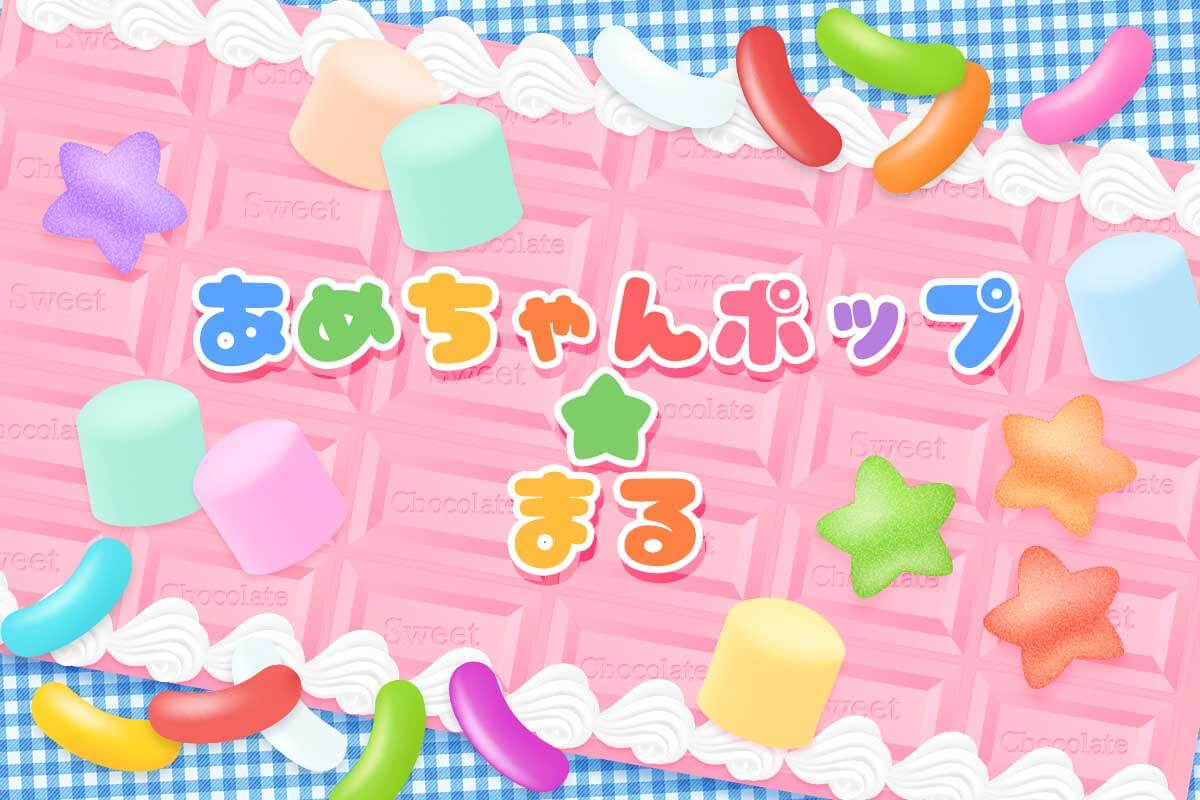
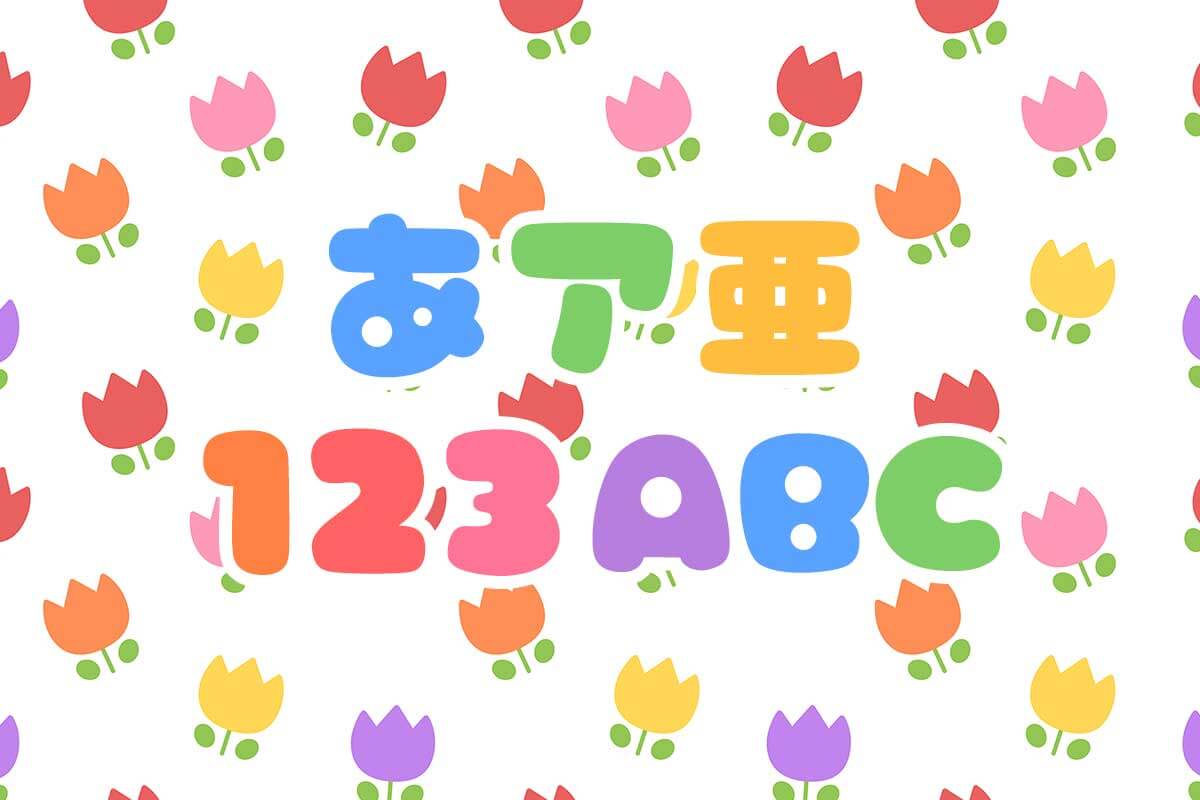
虹みんちょう
ちょっとレトロな雰囲気の明朝体フォントです。
漢字はJIS第一・第二水準・IBM拡張漢字(約6700文字)に対応しております。縦書き対応。
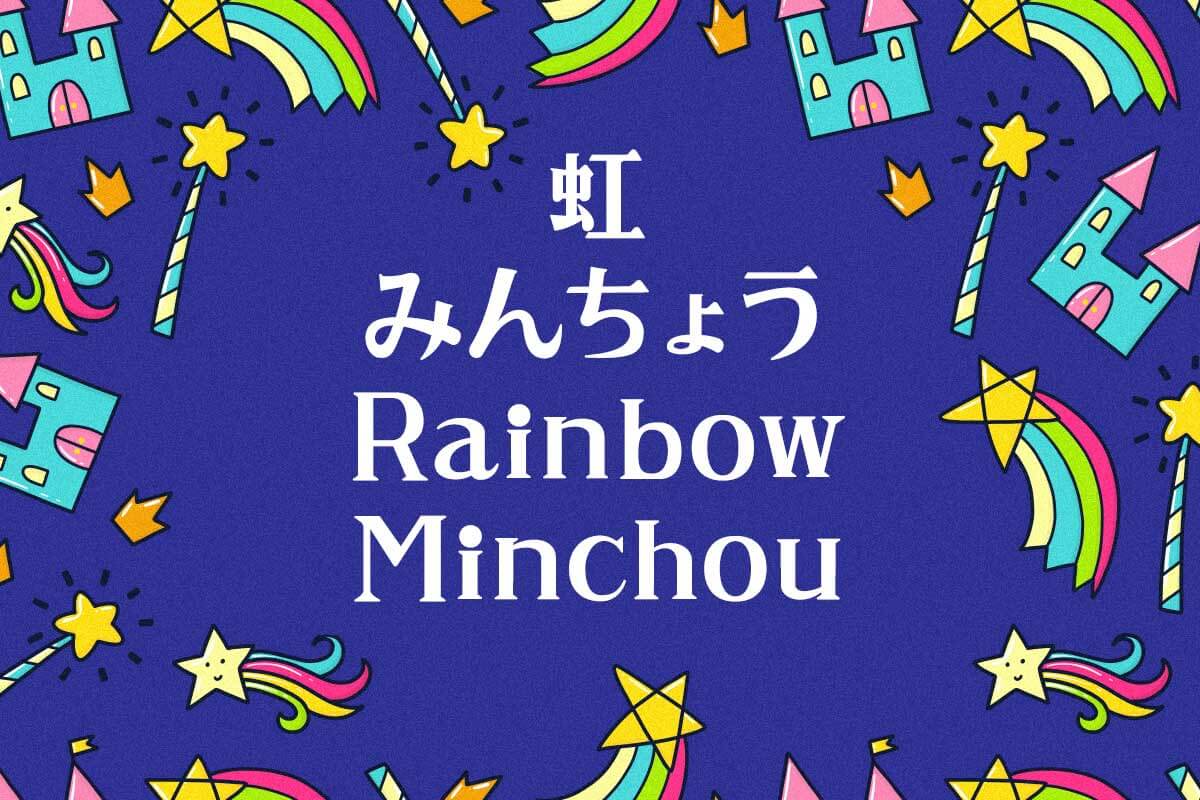
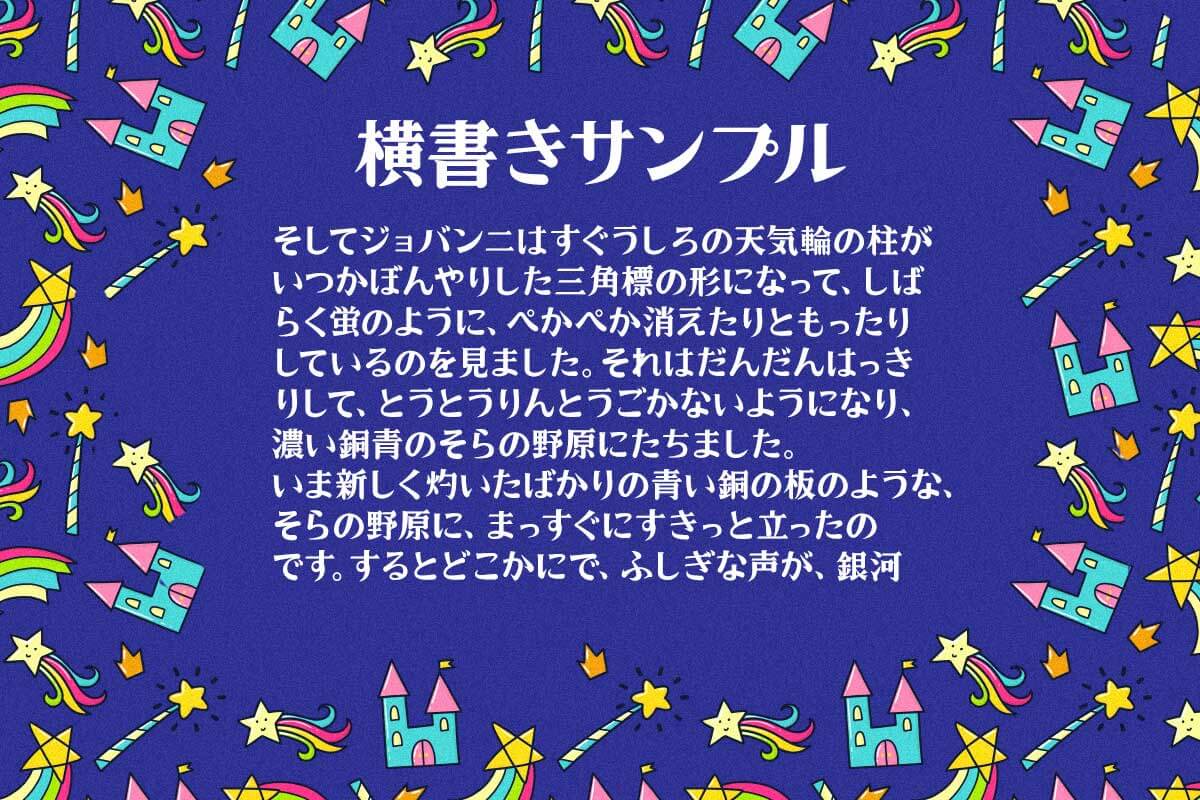
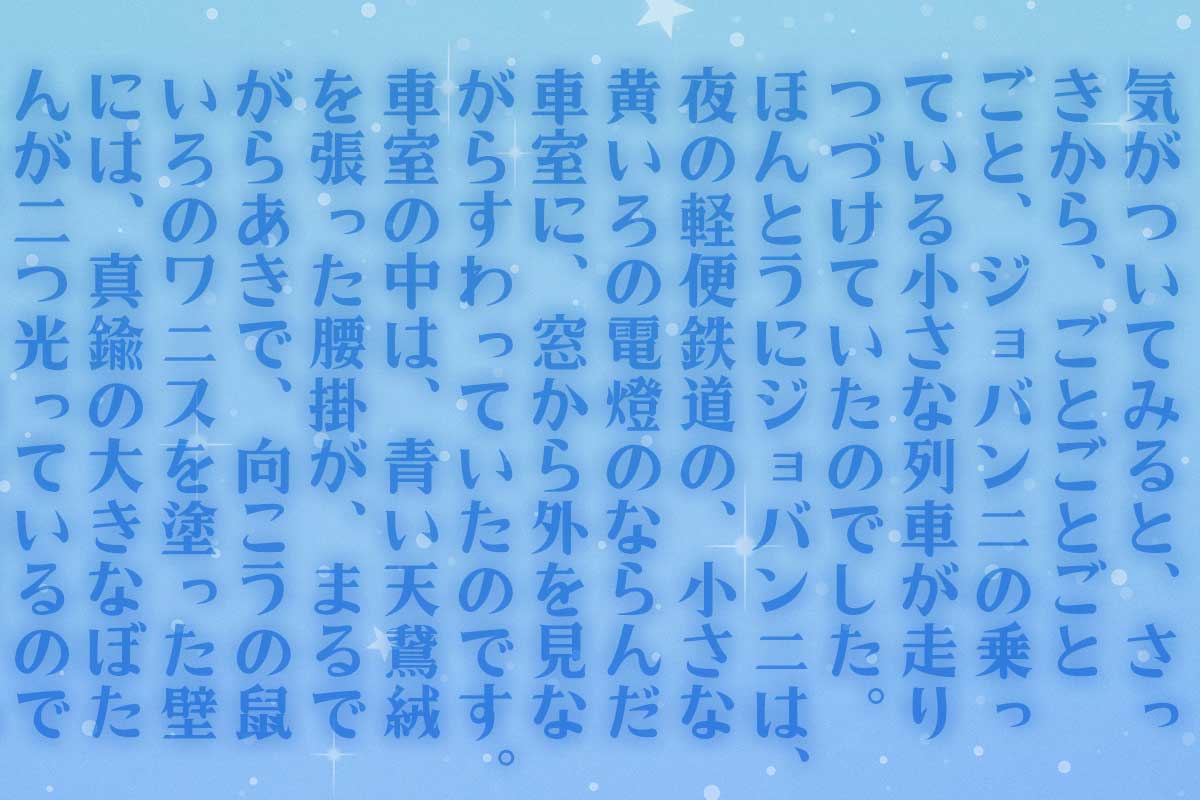
夜空みんちょう
あちこちに星やキラキラを散りばめた、夜空をイメージした明朝体フォントです。
漢字はJIS第一・第二水準・IBM拡張漢字(約6700文字)に対応しております。縦書き対応。
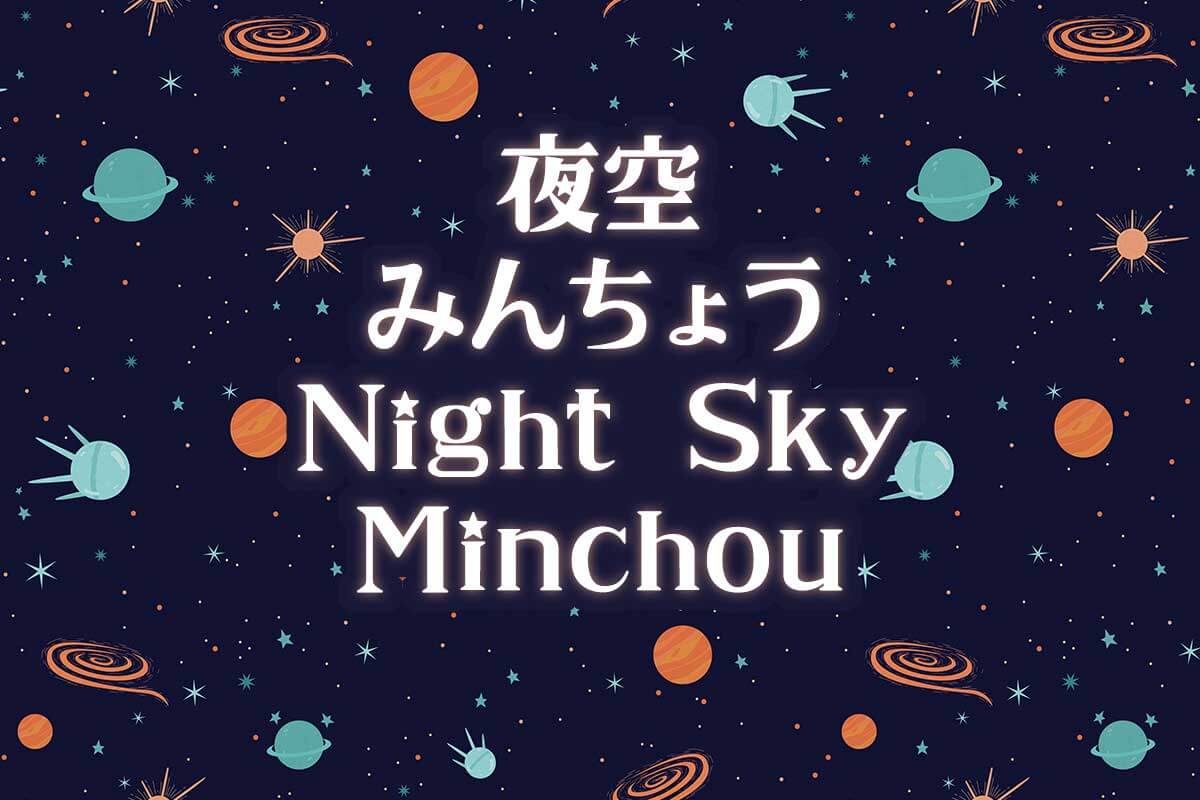
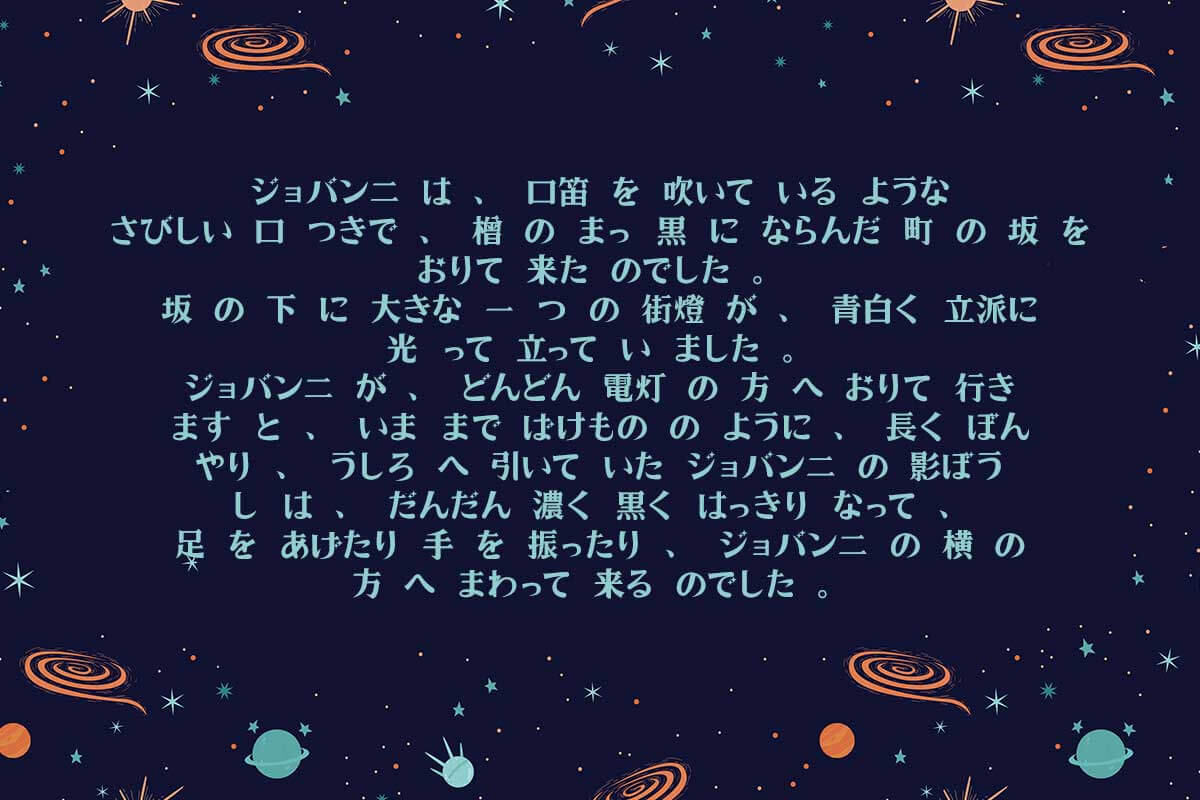
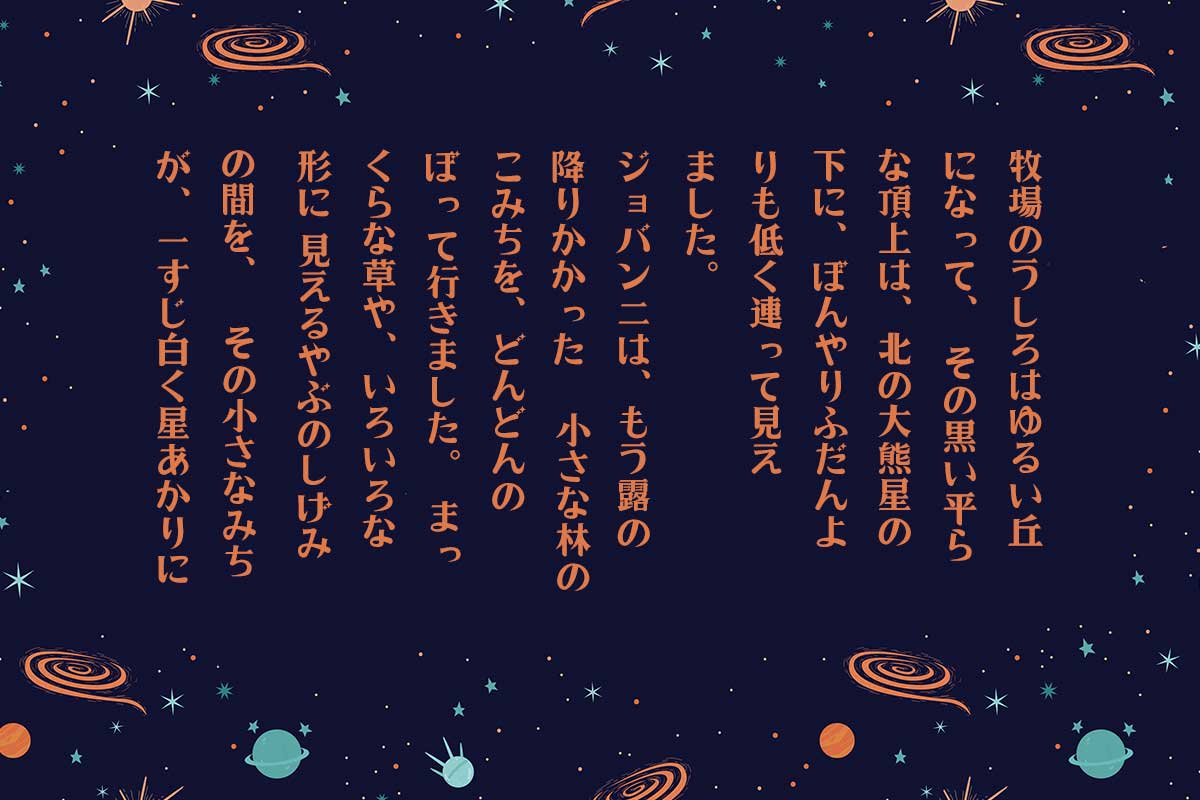
はちまるポップ
80年代に流行した丸文字をイメージしたフォントです。
漢字はJIS第一・第二水準・IBM拡張漢字(約6700文字)に対応しております。縦書き対応。
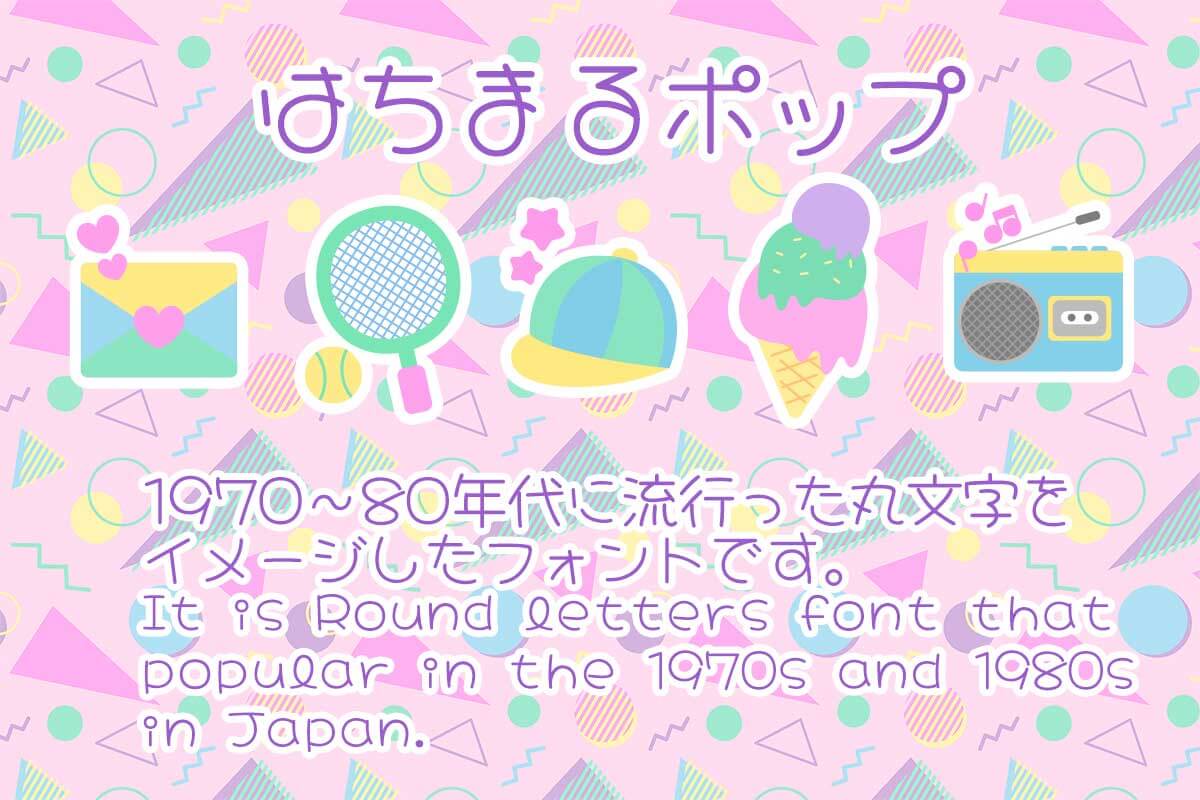
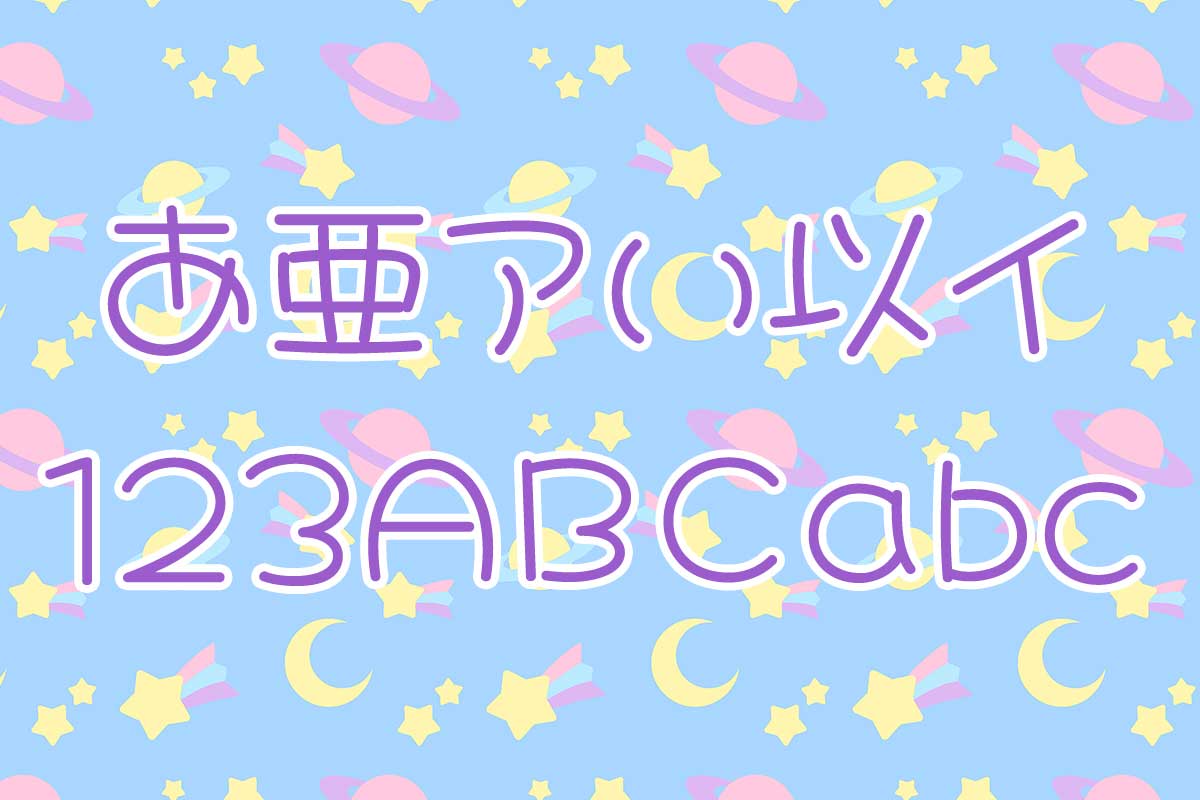
ましゅまろポップはーと
ハートをあちこちに散りばめた、ポップで太めの丸文字フォントです。
漢字はJIS第一・第二水準・IBM拡張漢字(約6700文字)に対応しております。縦書き対応。